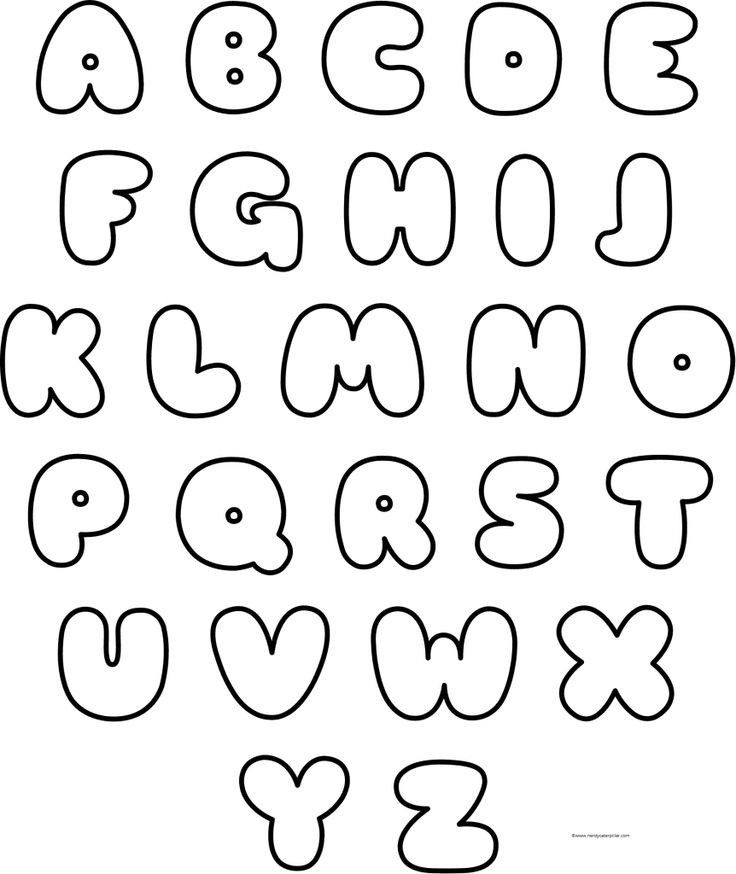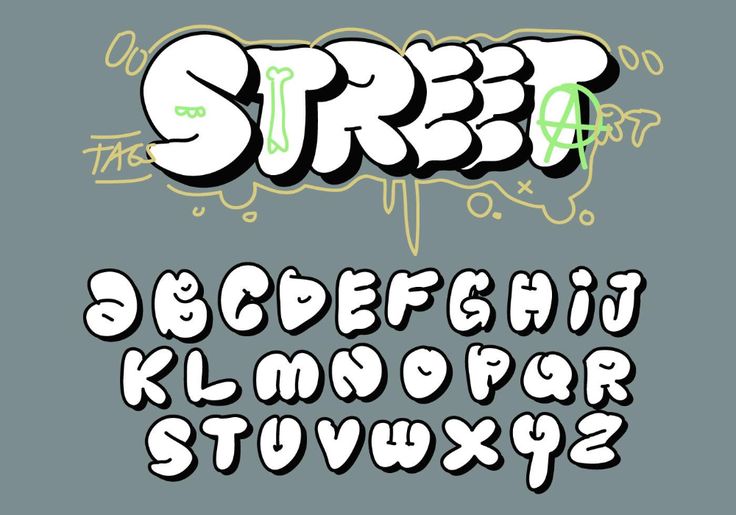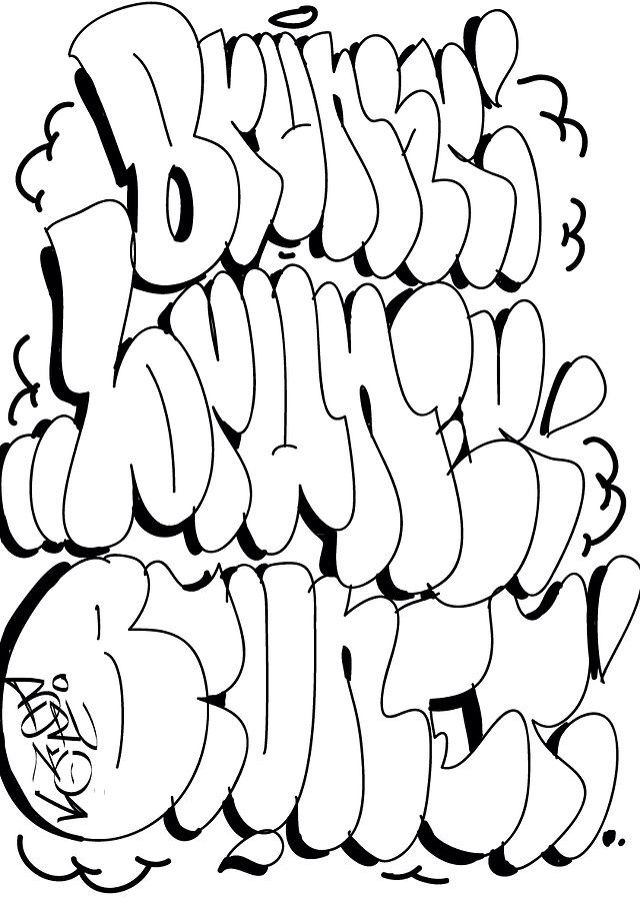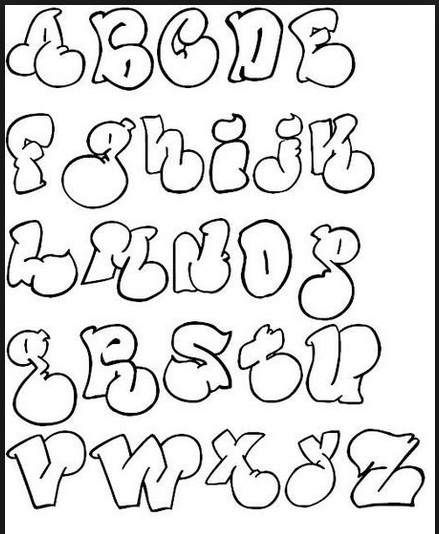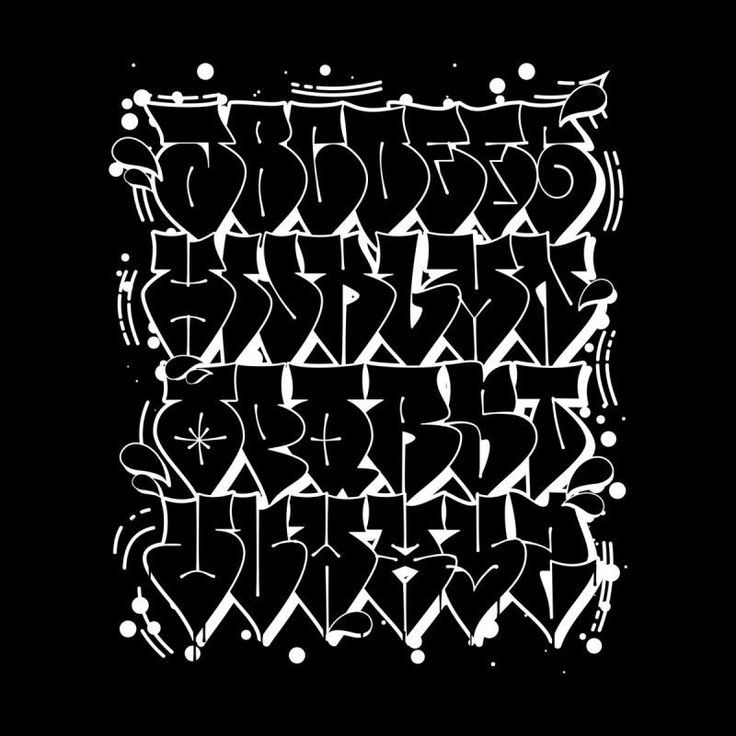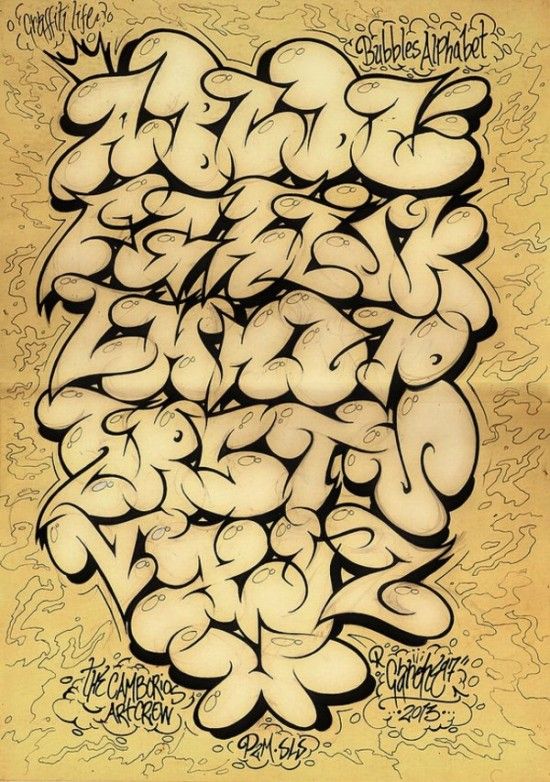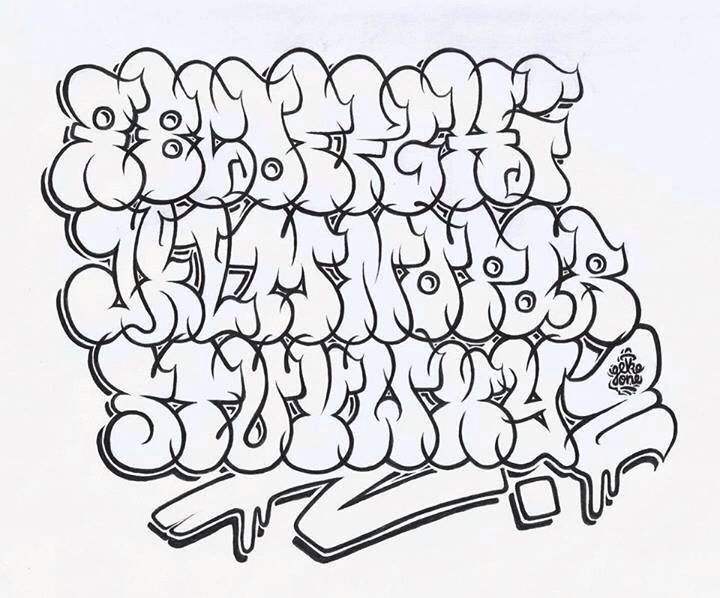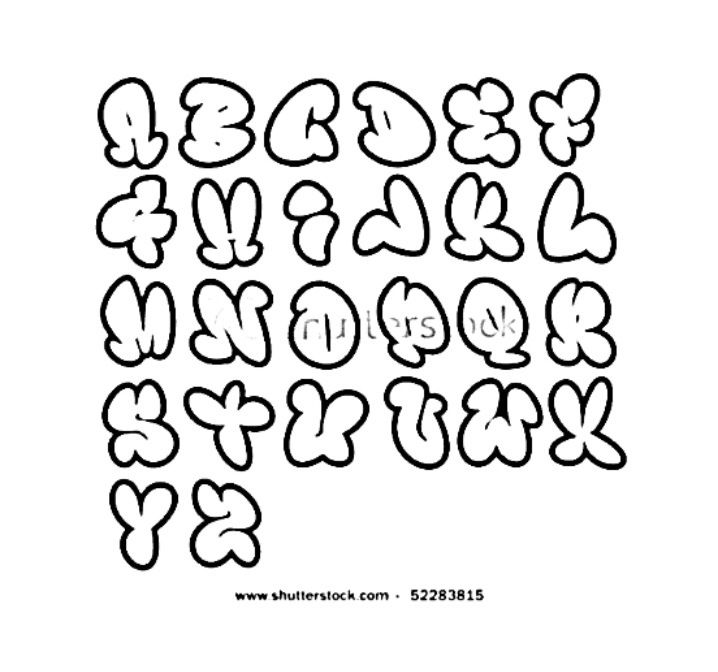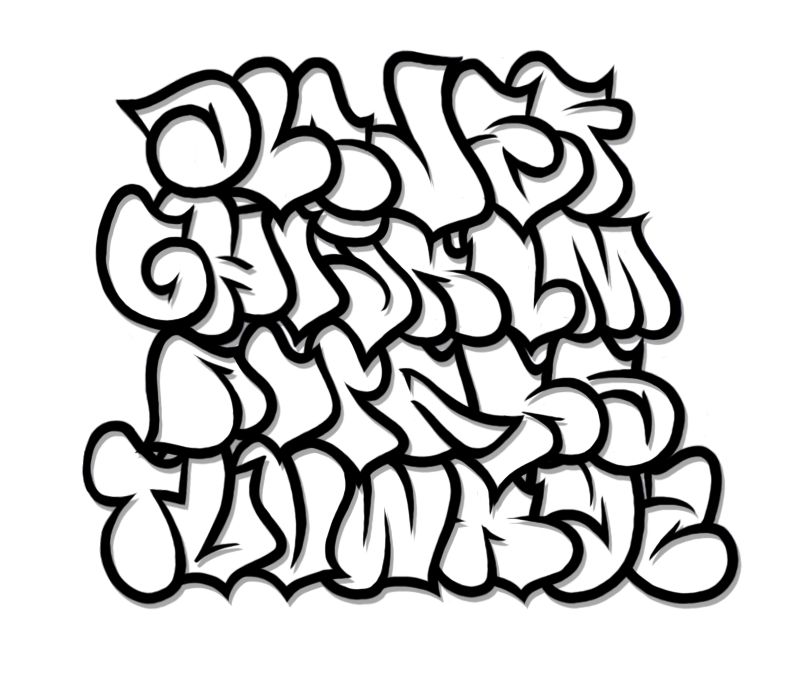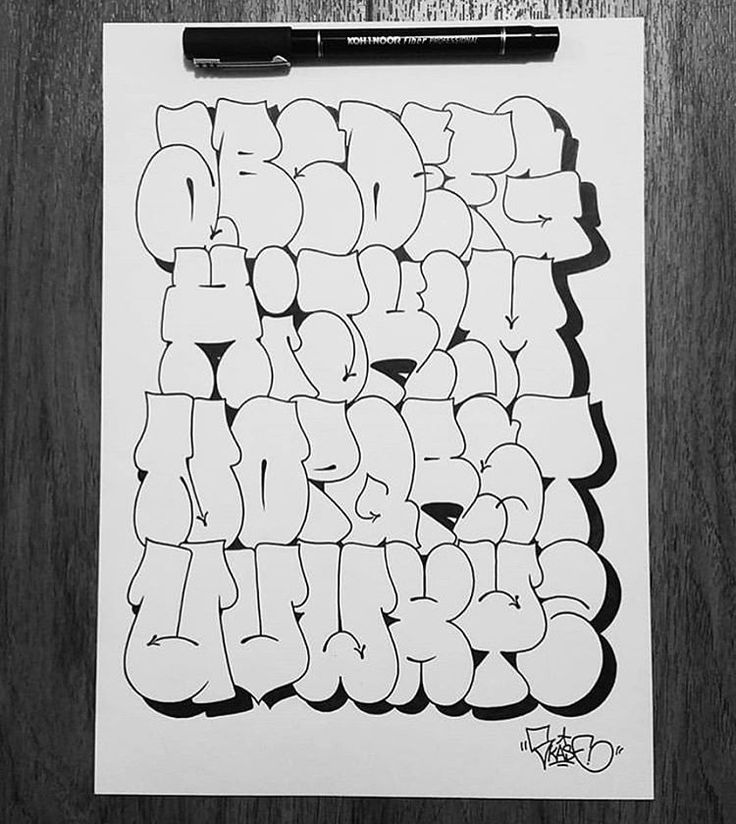
Бабл граффити — Простые объемные шрифты в стиле Bubble
Бабл граффити — это одно из первых направлений в прорисовке букв уличными художниками. Название связано с характерным способом их изображения. Буквы делаются похожими на пузыри. По-английски bubble означает «пузырь». Решение рисовать буквы именно такими пришло спонтанно. Любой человек, который не умеет рисовать, но хочет создать надпись, буквы которой будут стилизованы, сможет воспользоваться этим рецептом. Все черты нужно делать округлыми, толстыми и мощными.
Характерно, что изначально такой шрифтовой гарнитуры не было ни в одной стране мира, а появилась тенденция изображать алфавит в виде пузырей только благодаря стараниям уличных художников. В настоящее время можно скачать более 250 компьютерных бабл-шрифтов, и все они представляют собой изменение дизайна привычных гарнитур в сторону к дизайну стрит-арта.
Почему буквы такие кругленькие?
Округлость шрифта позволяет написать не только отдельную букву, но даже целую фразу без отрыва, на одном нажатии на головку баллончика с краской. Поэтому бабл стиль в граффити неразрывен с диким стилем и бомбингом. Для того чтобы стали получаться такие буквы не нужна очень уж долгая тренировка. Достаточно покататься по району на скейте в течение пары дней и оставлять свой тег везде и всюду.
Если буквы будут находиться на некотором расстоянии друг от друга, то получится более традиционный Бабл стайл, а если налезать друг на друга, надпись будет гнуться, смешение букв затруднять чтение, то художника можно поздравить — он стал мастером дикого стиля, очень популярного когда-то в США, а особенно в Нью-Йорке, а если быть более точными, то в Гарлеме и Бронксе, откуда дикий стиль и начал своё победное шествие по миру.
Некоторые Российские художники стремятся использовать кругленькие буквы стиля бабл в качестве основы, наделяя их какими-то дополнительными свойствами.
Немного истории…
Некоторую неуловимость, которую имеет bubble letter style, можно понять, если попытаться найти основоположников или наиболее ярких представителей стиля. Вы найдёте всех родоначальников граффити из США. Так рисовал Ричард «Ричи» Мирандо, известный как Seen UA. Действительно — его буквы могли быть толстенькими, но у кого они такими не были? С таким же успехом можно сказать, что Seen работал ещё и в диком стиле, потому что многие литеры его работ переплетаются между собой.
Так работал и Cope 2, как подписывался американский художник из Нью Йорка Фернандо Карло. Они упомянуты в основном в силу того, что являются одними из наиболее известных представителей рисования аппетитных толстеньких букв, но какие-то подобные оставили на стенах почти все райтеры 80-ых годов, и оставляют до сих поколения новых волн представителей стрит-арта.